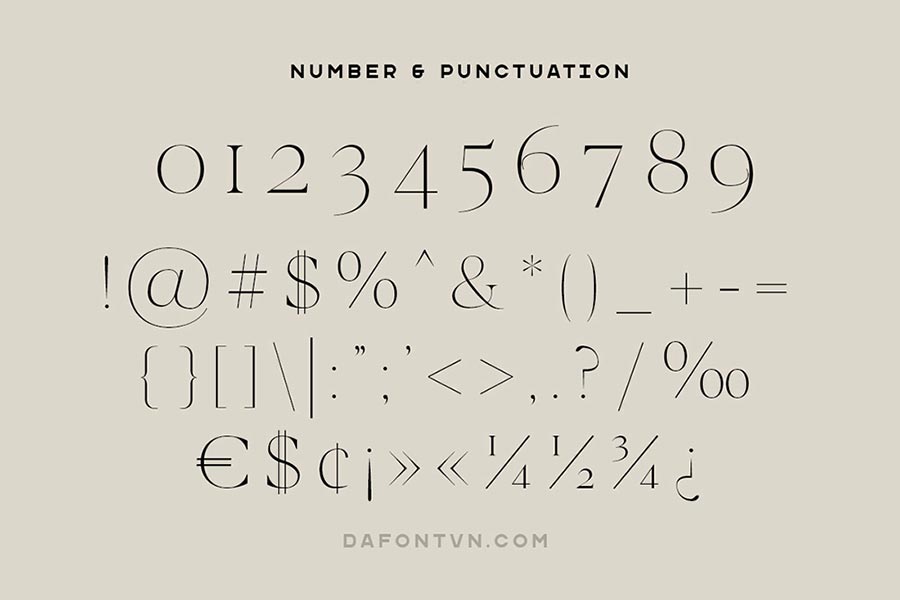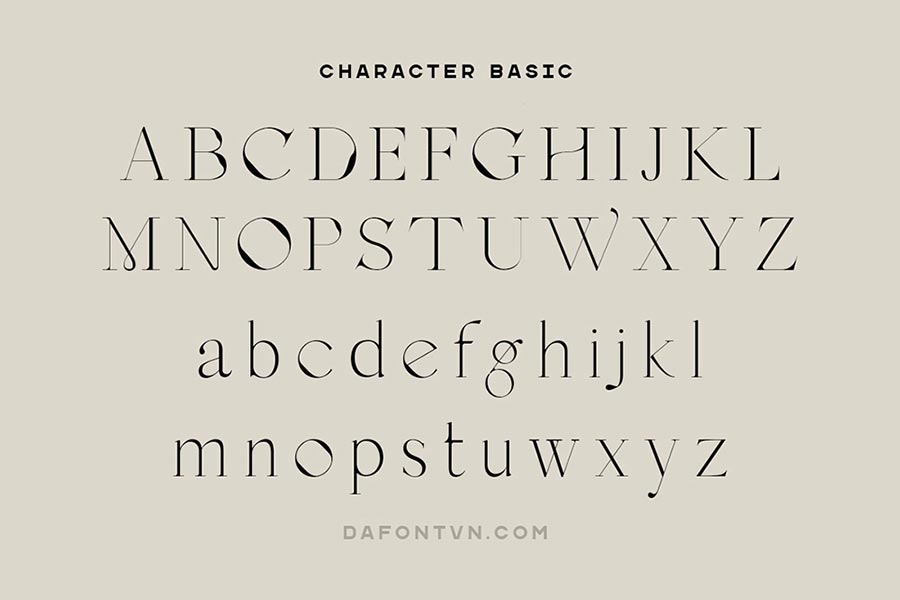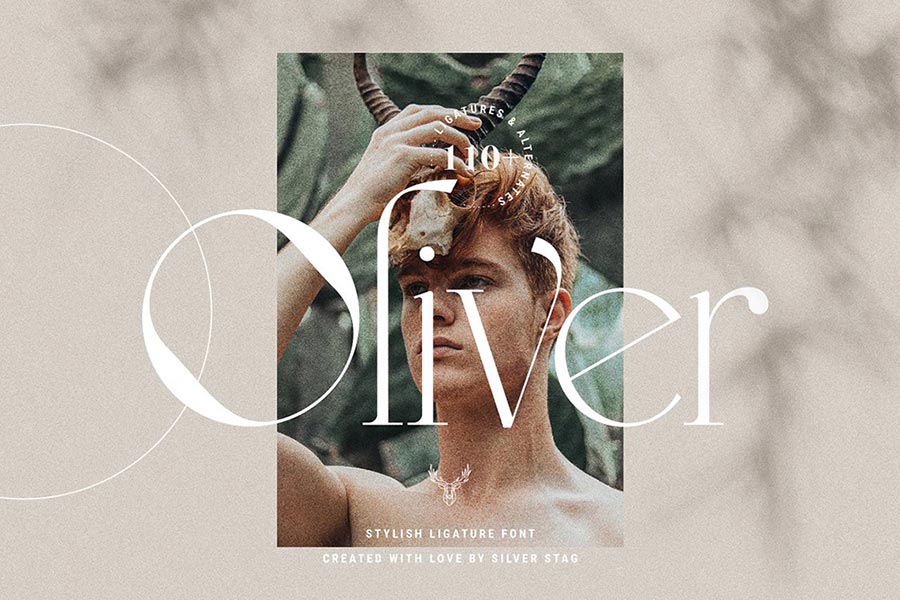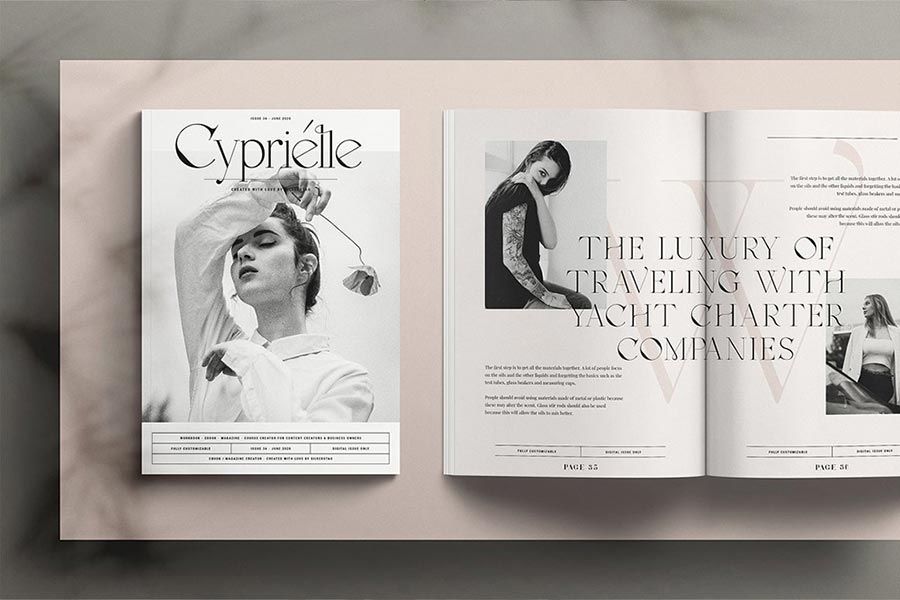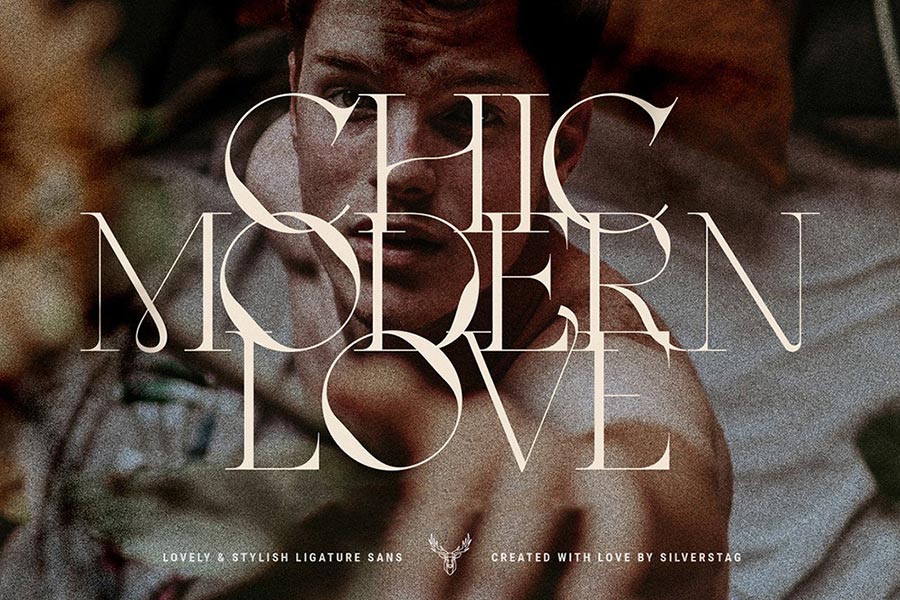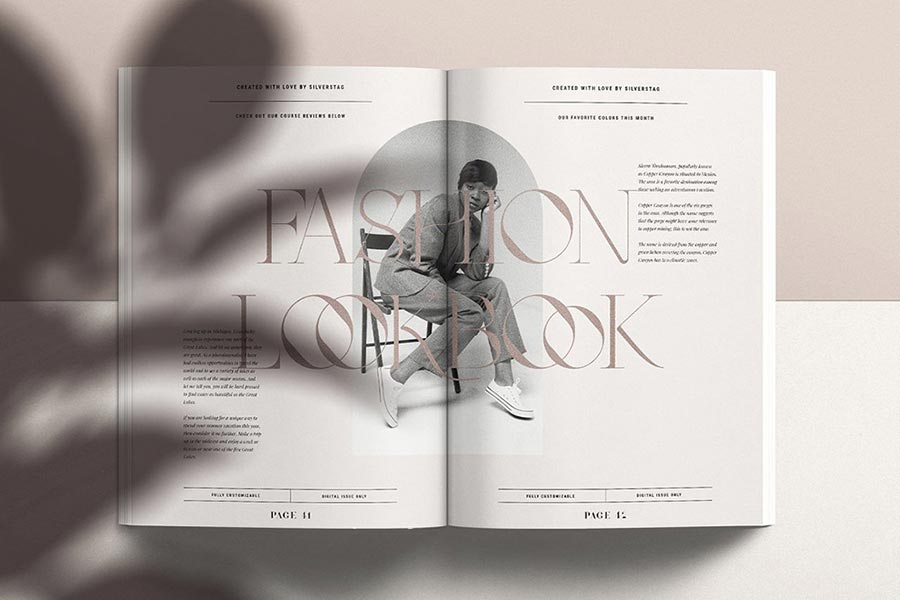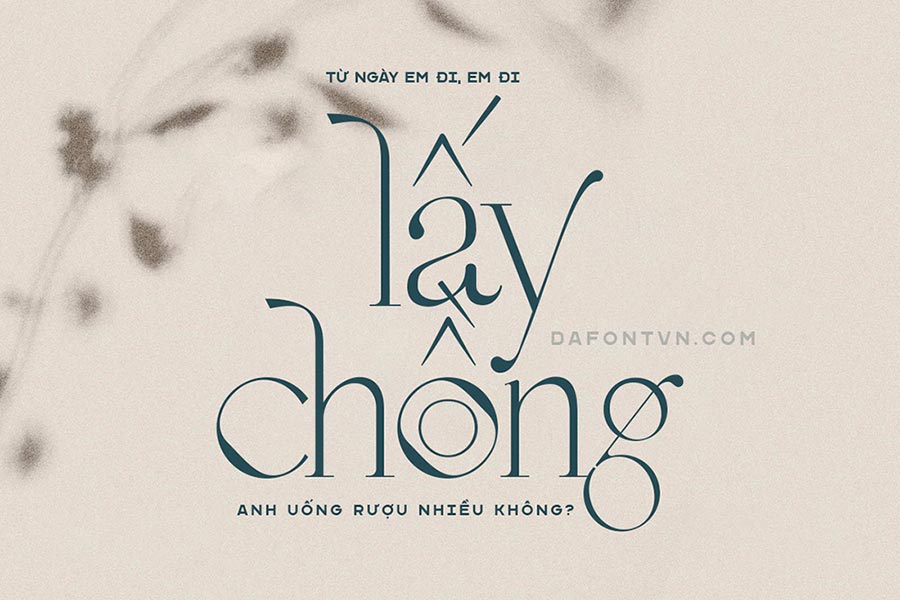
Chia Sẻ Miễn Phí Font Việt Hóa - MOON CROWD Mang Phong Cách Sang Trọng Và Hiện Đại
Trong thiết kế đồ họa, việc lựa chọn một font chữ phù hợp là một yếu tố quan trọng, giúp truyền tải thông điệp và tạo ấn tượng mạnh mẽ với người xem. Một trong những font chữ mới được yêu thích trong cộng đồng thiết kế hiện nay là MOON CROWD, đặc biệt khi phiên bản font này đã được Việt hóa để phù hợp với nhu cầu của thị trường Việt Nam. Với phong cách sang trọng, hiện đại, và dễ sử dụng, MOON CROWD hứa hẹn là sự lựa chọn hoàn hảo cho nhiều loại thiết kế, từ các ấn phẩm quảng cáo, website, đến các dự án thương hiệu, bao bì và sự kiện.
1. Phong Cách Sang Trọng và Hiện Đại
MOON CROWD mang đến một phong cách thiết kế tinh tế, hiện đại với những đường nét mượt mà, thanh thoát. Được thiết kế để phù hợp với nhiều loại hình thiết kế khác nhau, font chữ này thể hiện sự sang trọng qua các đường cong mềm mại kết hợp với các ký tự có độ rộng vừa phải, không quá thô cứng, tạo cảm giác nhẹ nhàng nhưng vẫn đầy ấn tượng. Font chữ này rất phù hợp với các thiết kế muốn thể hiện sự thanh lịch và đẳng cấp, như thiết kế thương hiệu cao cấp, thiệp mời, các chương trình sự kiện sang trọng, hoặc các ấn phẩm marketing hướng tới đối tượng yêu thích sự hiện đại và quý phái.
2. Tính Linh Hoạt Trong Sử Dụng
Một trong những điểm mạnh của font MOON CROWD là tính linh hoạt trong việc sử dụng. Với phiên bản Việt hóa, font chữ này có đầy đủ các ký tự và dấu tiếng Việt, giúp người thiết kế dễ dàng áp dụng vào các dự án nội dung tiếng Việt mà không lo bị thiếu sót. Font chữ có thể được sử dụng trong nhiều ngữ cảnh khác nhau, từ tiêu đề, slogan đến đoạn văn bản, mang lại sự đồng nhất và mạch lạc trong toàn bộ thiết kế. Đặc biệt, với khả năng hiển thị rõ nét, MOON CROWD giúp các thiết kế trở nên dễ đọc và ấn tượng hơn khi nhìn từ xa.